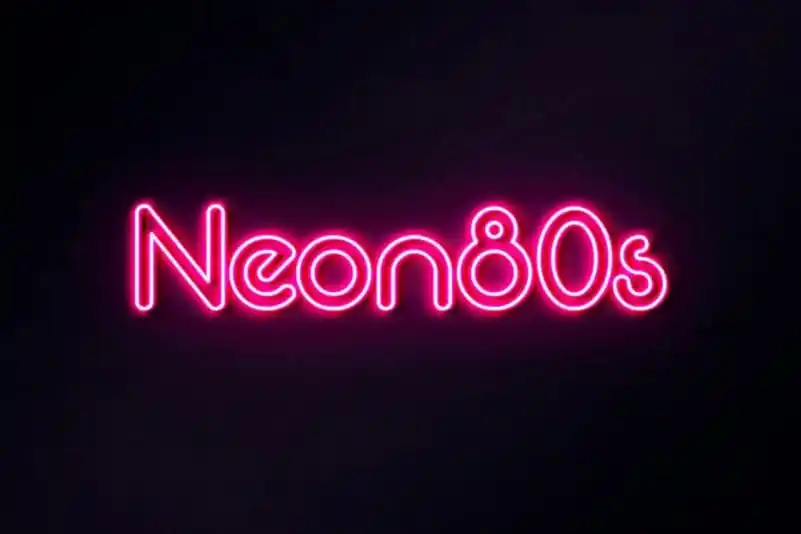
A Neon 80s Sans Serif é uma nova adição ao universo das fuentes modernas inspiradas no design futurista do neon dos anos 1980. Desenvolvida pelo designer Parviz Guliyev, esta fonte evoca os efeitos de luz vibrantes encontrados nas grandes cidades daquela era com seu estilo minimalista, apresentando formas de letras com ângulos limpos e bordas suaves, exatamente como se fossem neon. Uma característica inovadora desta fonte é que ela segue o formato de linhas retas que abrem e fecham a partir de pontos bem definidos, verdadeiros retratos dos tubos de neon da época. Ideal para dar um toque único em design gráfico ou projetar realmente os famosos sinais luminosos do passado, a Neon 80s Sans Serif oferece uma opção única para criar ambientes futuristas e vibrantes.